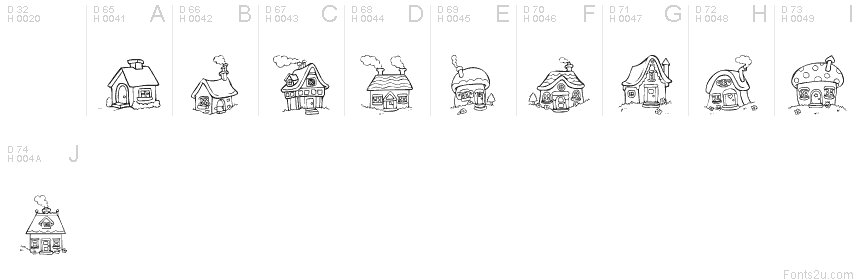
Destiny's Little Houses to darmowy font typu dingbats w kreskówkowym stylu, który wypełni Twoje strony uroczym, małym miasteczkiem. Każda ikona wygląda jak odręcznie naszkicowana czarnym tuszem — z krzywymi dachami, puszystymi chmurami i kominami przypominającymi bazgroły — dzięki czemu Twoje projekty od razu zyskują przyjazny, baśniowy klimat bez konieczności tworzenia własnych ilustracji.
Destiny's Little Houses doda uroku dziecięcym kartom pracy, plakatom szkolnym, stronom w albumach, kreatywnym pocztówkom z ofertami nieruchomości, ulotkom osiedlowym, blogowym nagłówkom czy naklejkom w mediach społecznościowych. Ten darmowy font najlepiej prezentuje się, gdy użyjesz dingbatsów w nieco większym rozmiarze jako obramowania lub separatora; połącz go z czystym krojem bezszeryfowym w tekście, aby domki pozostały wyraźne i czytelne.